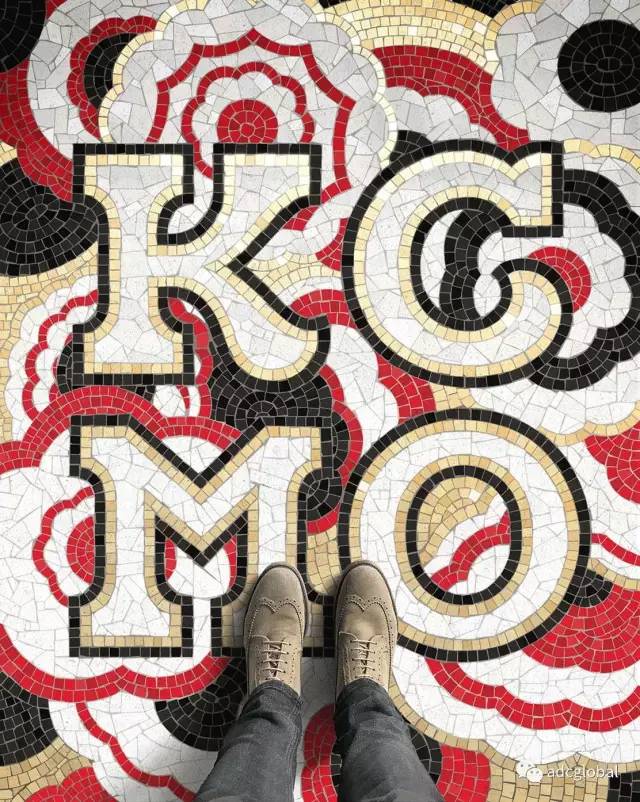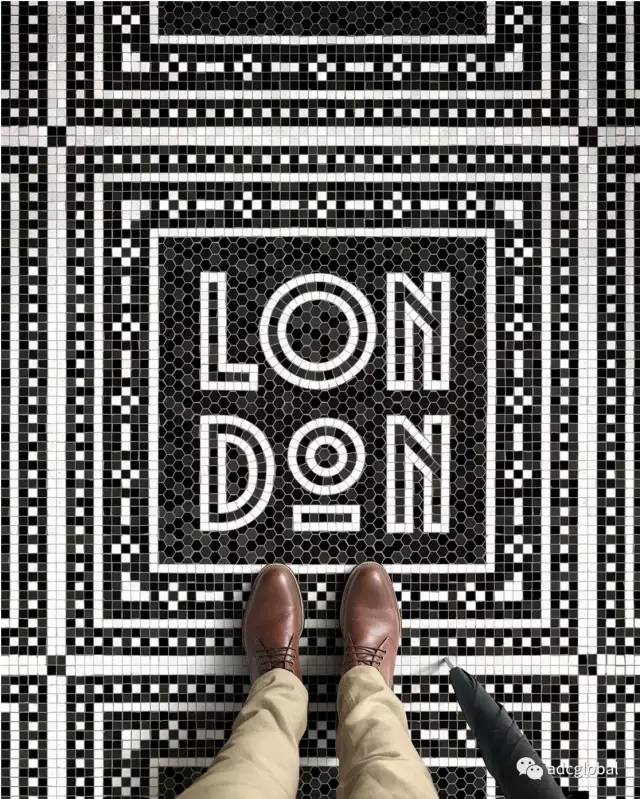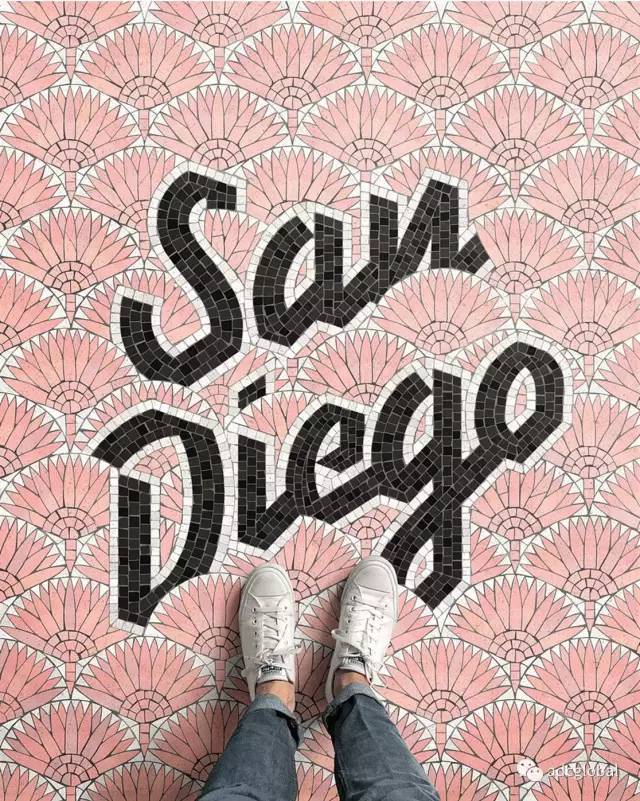
[YOUNG GUNS映象]马赛克地砖字体使用案例
马赛克地砖总能给各种各样的公共空间带去活力及生气。
尤其是在火车站、地铁站这些作为交通枢纽存在着的公共空间中。
许多世界知名的火车站和地铁站的马赛克地砖就像万花筒一样有着华丽多变的图案和颜色。
现在、甚至有些旅行团会将带人们去走访这些纽约城中“最美丽的地砖设计”作为旅程的一部分。
纽约当地设计师、作家、 Young Guns 12 的获奖者 Nicholas Misani 也采用了“马赛克地砖设计”这种艺术形式来完成他的新作品―Fauxsaics(用不同马赛克地砖字体设计代表不同的城市)
在此,我们有机会得以和Nick探讨、了解到他的新作。
Q:这个项目的想法最初来源于哪里呢?
老式车站,酒店大堂(内外)地面上的旧马赛克字体,一直都很让我着迷,但直到我开始为 ADC 名人堂奖得主Louise Fili 工作后,我才真正开始欣赏它们。
Louise是传统排版设计大师的同时她也致力于研究数字马赛克字体很多年了,所以她是我这个项目的很大一部分成因。
当和她一起为她的两册新书 《Graphique de la Rue》、《Gràfica de les Rambles》忙碌的时候,我有幸能够每天看到各种华丽的马赛克字体的照片。
为了使这些字体能被更好的收录进书中,我会花很多的时间去用数码化在电脑里尽可能修复这些马赛克字体,有时也不得不原创那些真实马赛克字体上残缺的或是被遮蔽起来的区域。这些年发展的电脑技术已经完全可以克服这个问题了,并且能使完全原创的部分看起来十分的自然。
Louise告诉我,因为我是意大利人,所以我很擅长创建马赛克字体―意大利有着数千年的马赛克字体历史。但我知道最主要的原因还是因为我有她这样的一位好老师。此外,我还想提及一位在我创作的开始阶段一直激励和支持我的朋友―― Lauren Hom。
最近, Lauren正在教授一堂有关’富有激情的项目’的课,她鼓励她的学生们大量的反思以及横向思维。
我也尝试着用这种思维来思考我的项目,我能想到的马赛克字体能吸引我的三个最根本的点可能是“字体”“装饰艺术”“室内设计”。
Q:和我们说些创作的过程吧
我用 Illustrator 来计划和准备我的设计。我在Illustrator里确定图块的大小、形状以及将会使用的不同的平铺模式。考虑每个设计由 6000 到10,000个小部分拼贴而成,所以这一准备阶段格外的耗费时间。
之后,我会使用 Photoshop添加一个或两个纹理和一些微妙的灯光效果,其中,金属效果尤其耗费时间。
最后,我也会用iphone拍一些鞋子的素材来制造出画面的场景感来完善这个创作。
Q: 让这些马赛克字体看起来真实的最大的挑战是什么?
挑战有很多,在现实的切割过程中,瓷砖的平滑曲线切割是很难达到。
所以在现实中,即使遇到曲线设计的时候,大部分瓷砖的线条也倾向于用方形呈现。每一块瓷砖的颜色也需要极为巧妙地调整,同时,也需要把握整体的光照效果,让整体看起来自然不会太违和。
另外,还需要符合传统的技术去构想。当然,其中最难的部分还是使用photoshop调整时需要掌握一个度,不能过度的调整。
Q: 你是如何选择想要表现的城市的?你有实地去过这些城市吗?还是这些设计完全源于你的想象力?你下一个想要表现的城市是?
我在“Fauxsaics”(http://fauxsaics.com/ )上贴的图大多数是为了即将到来的旅行。但当我已经用完了想去的目的地时,我开始使用我近两年所去过的那些能让我产生灵感的目的地。下一步我会去拉霍亚,之后也会回我的家乡米兰。我也会为米兰做一个马赛克字体。
Q:目前为止,你收到过哪些反馈呢?
我得到的反馈很多,大部分都是鼓励我进一步更深入的完成这个系列。